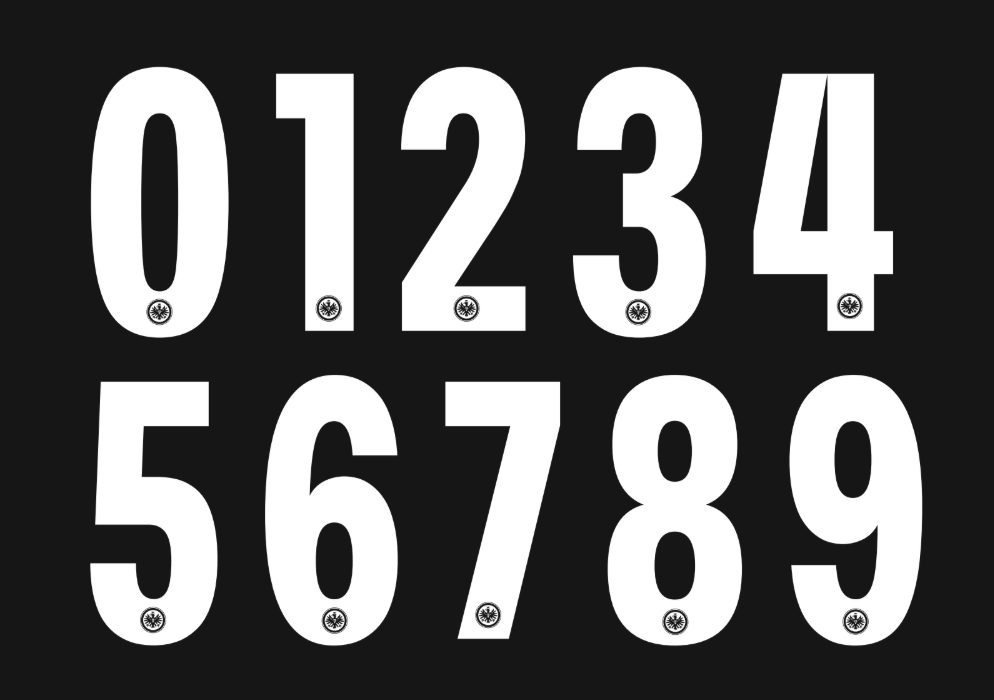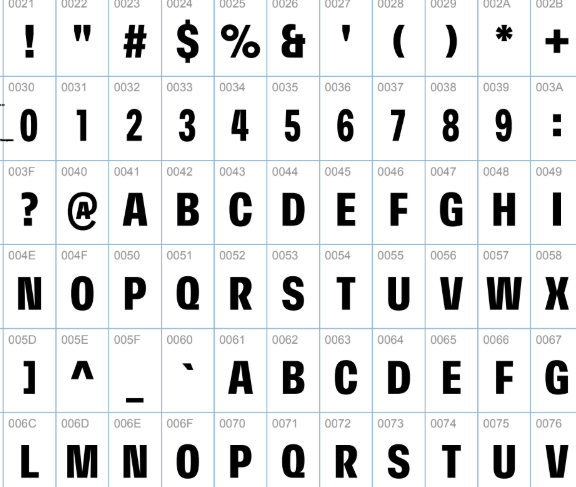
A tradição do futebol alemão se encontra com o design moderno. O Eintracht Frankfurt, conhecido apaixonadamente como Die Adler (As Águias), entra na temporada 2025/2026 mantendo sua parceria sólida com a Nike. O resultado é um uniforme que exige uma tipografia à altura da força da Bundesliga.
- Conteúdo: Alfabeto completo (caixa alta), numeração oficial e caracteres especiais da língua alemã (como o Umlaut).
Estilo Visual e Aplicação
A tipografia desenvolvida pela Nike para o Eintracht Frankfurt nesta temporada segue uma linha estética industrial e robusta, características marcantes do design germânico.
A fonte apresenta traços espessos e condensados, projetados para maximizar a visibilidade sobre as listras tradicionais em preto, vermelho e branco.
Os números possuem cortes angulares internos que conferem dinamismo e modernidade, diferenciando-se das fontes genéricas de catálogo. É o equilíbrio ideal entre a agressividade necessária em campo e a elegância de um time de elite europeu.